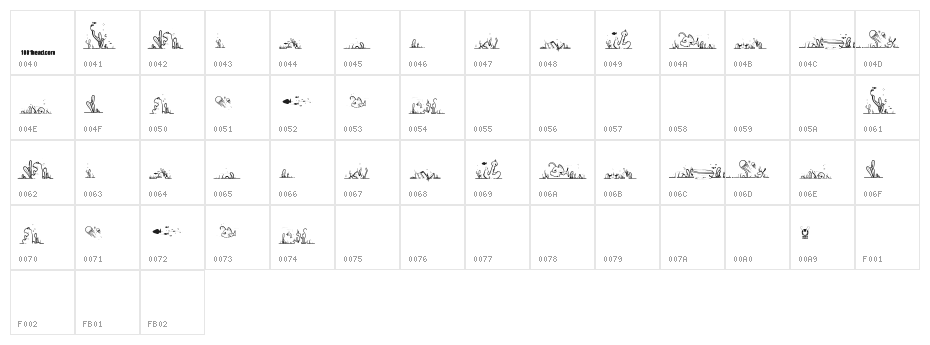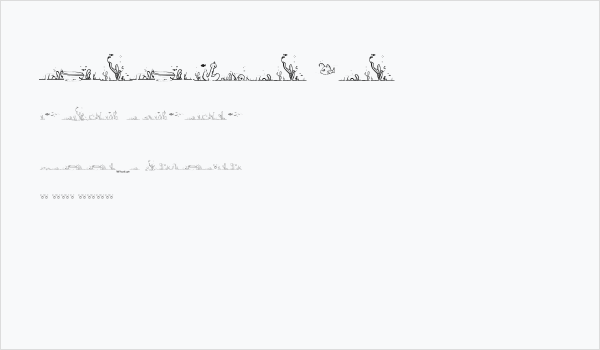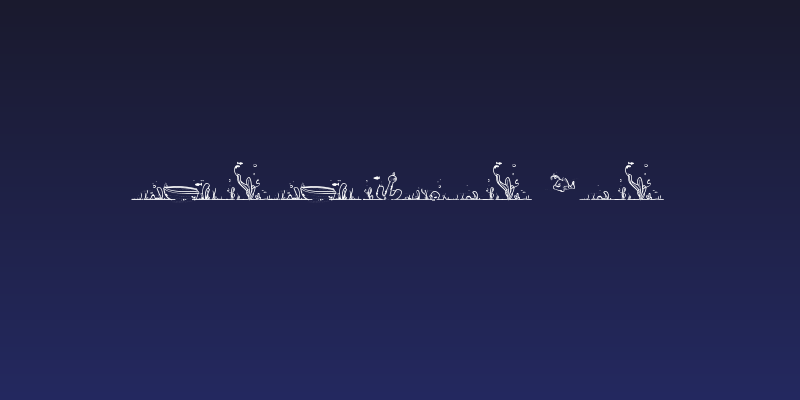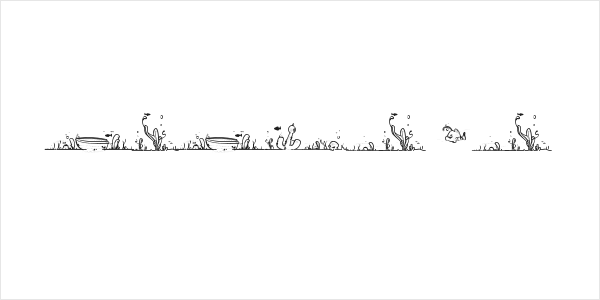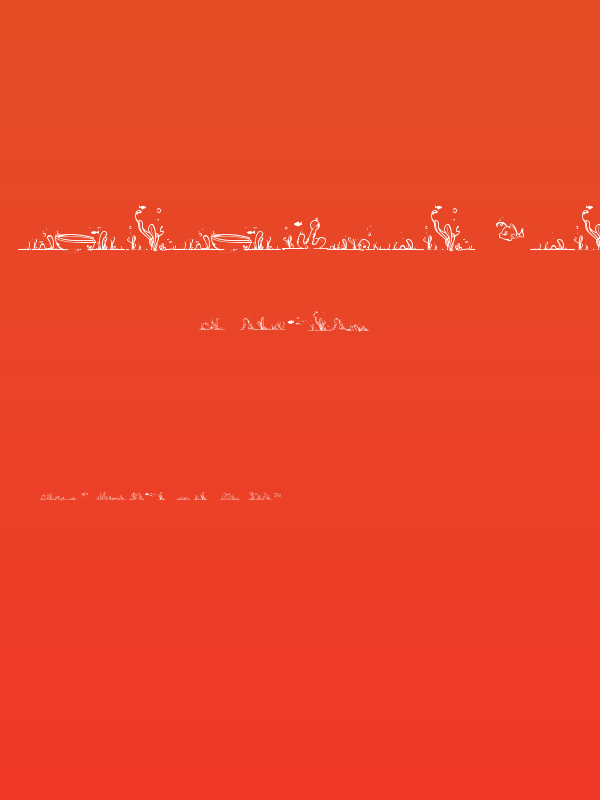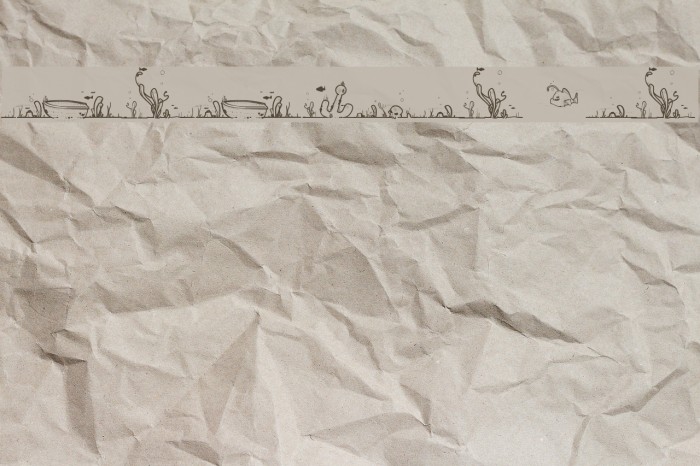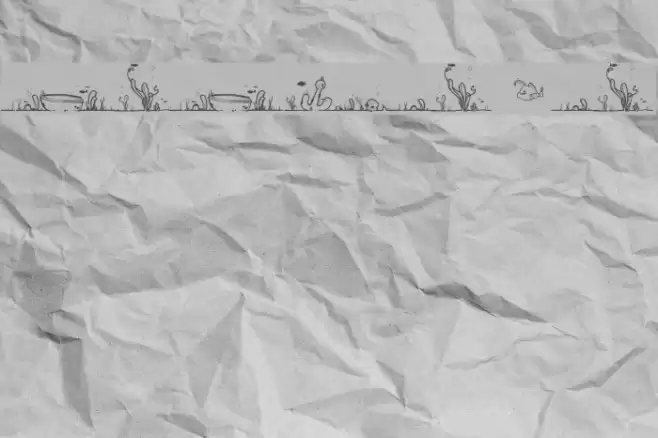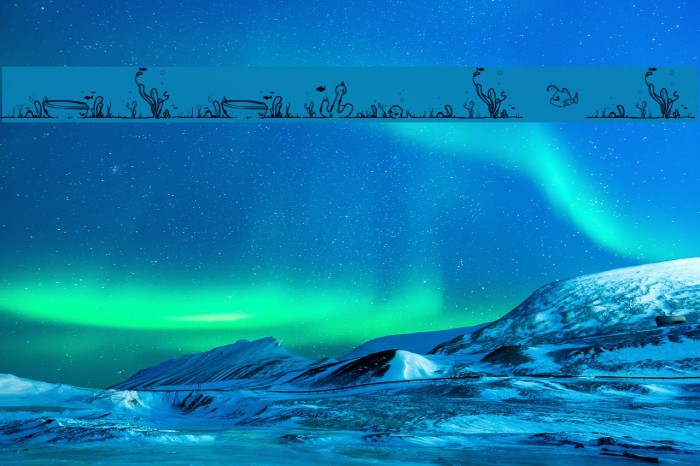
LaLinea Sea Font
| Область применения | Decorative borders, Artistic projects |
| Рекомендуемые проекты | This design could be used for decorative borders in children's books, ocean-themed event invitations, or artistic projects requiring a sea motif. |